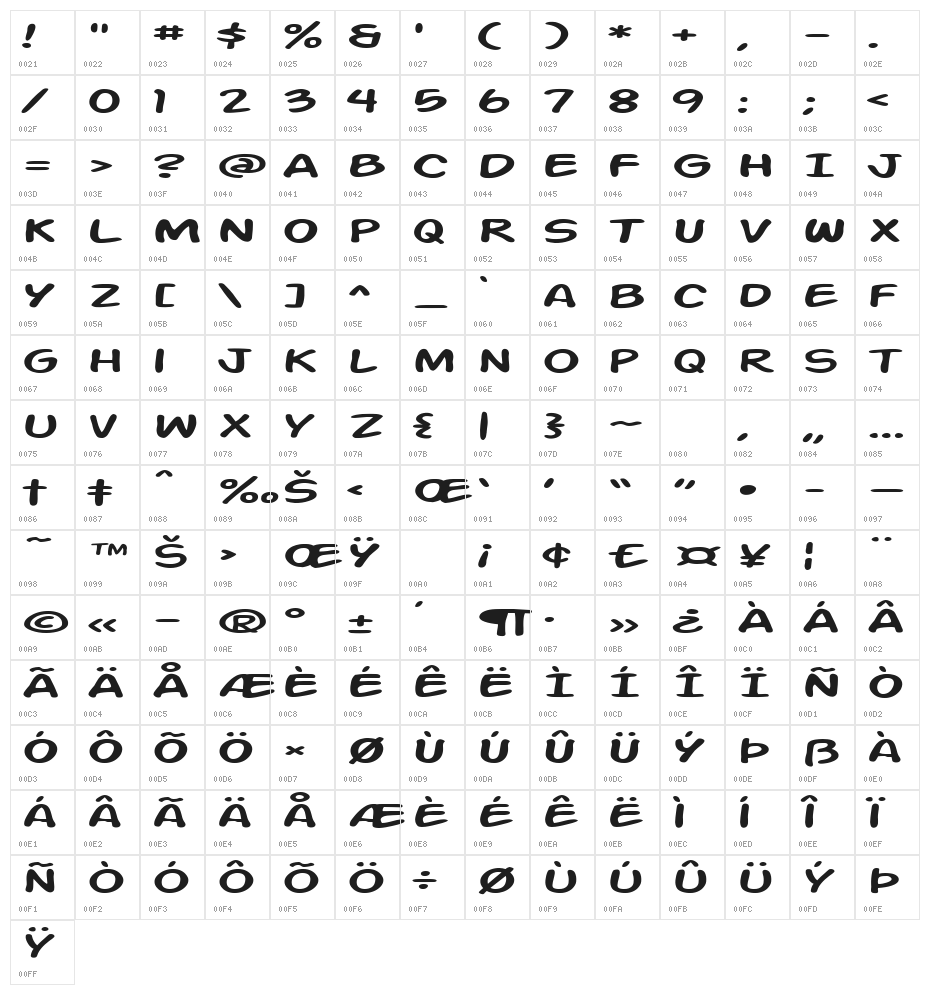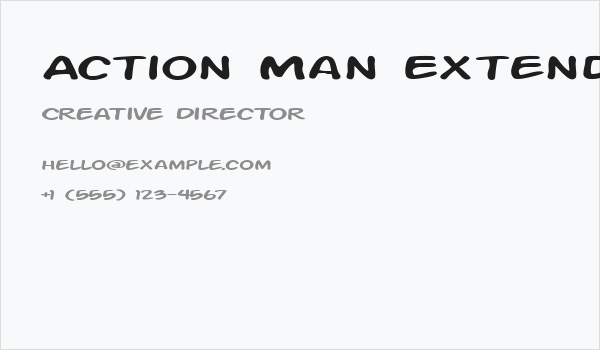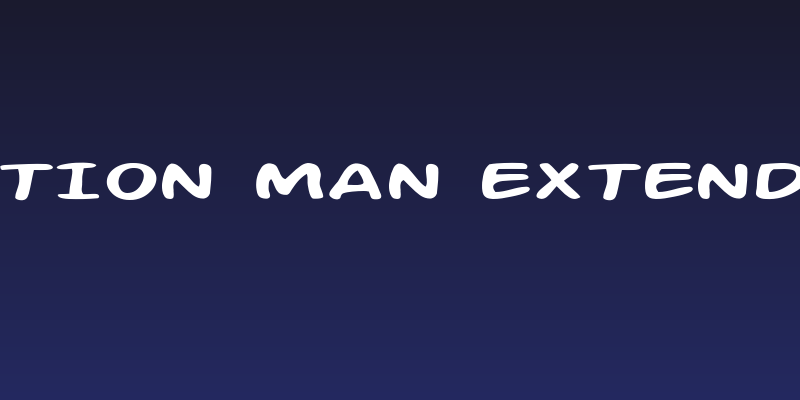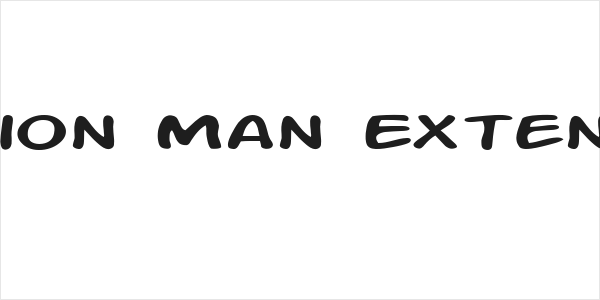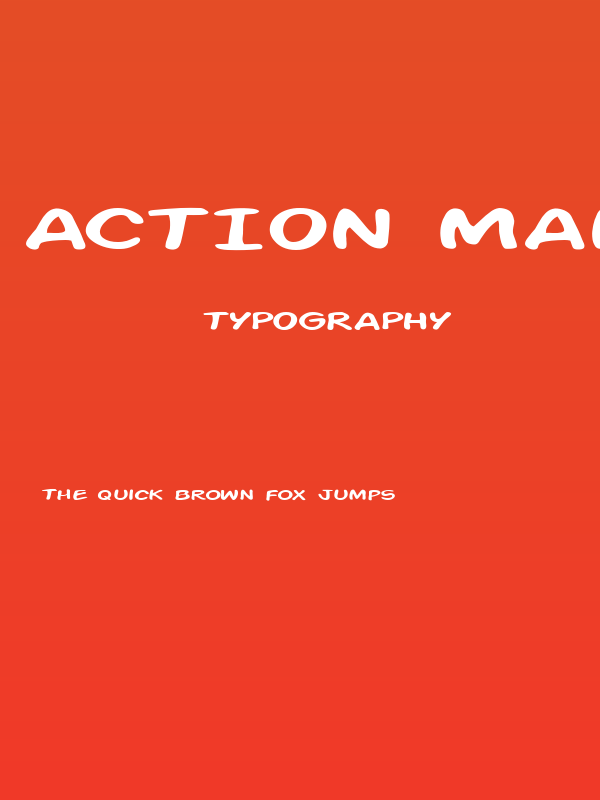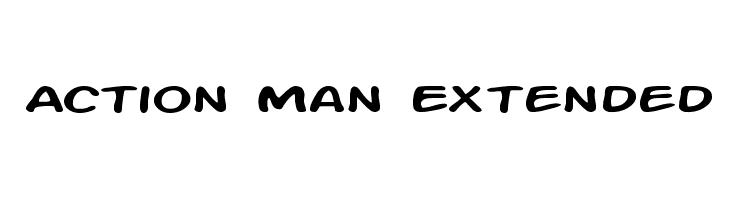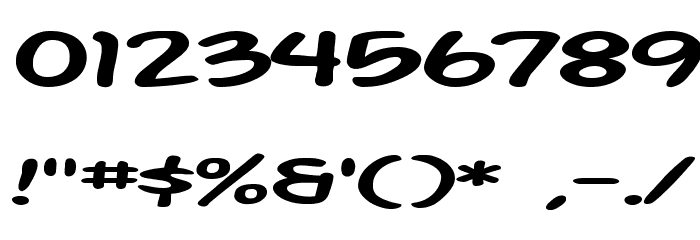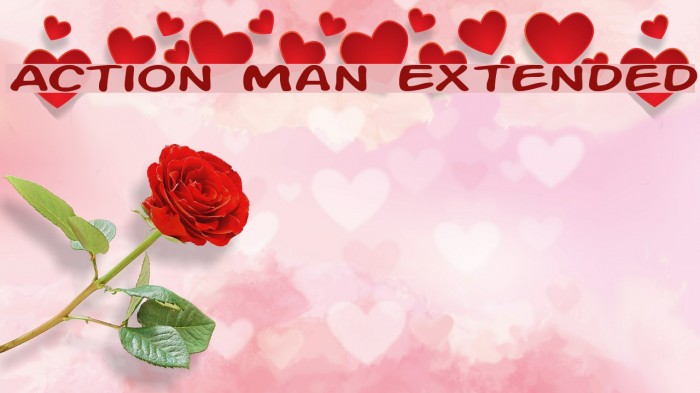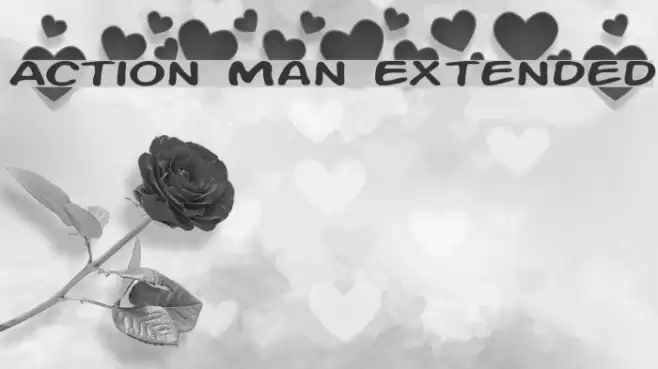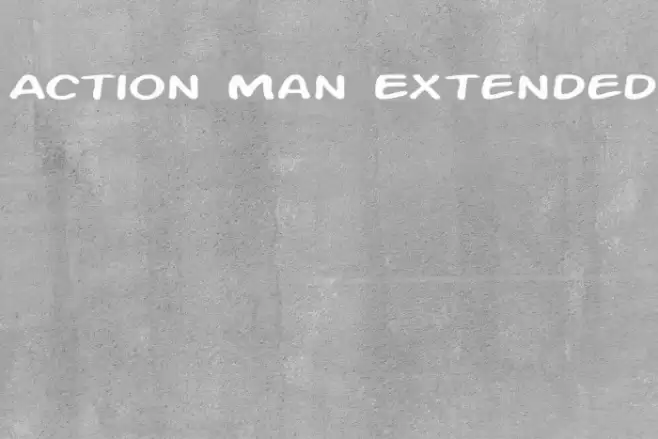
Action Man Extended Font
| Estilo geral | Playful, Casual |
| Projetos propostos | Ideal for children's books, playful branding, casual invitations, and fun posters. |